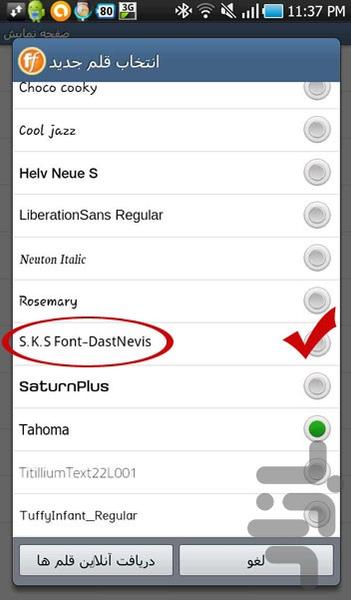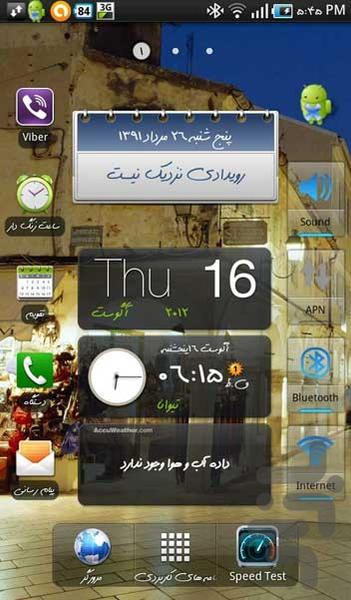
S.K.S-فونت دست نویس Samsung (اصلی)
فونت فارسی برای استفاده در گوشی های دارای سیستم عامل اندروید ، بسیار محدود و دارای تنوع کمی می باشد ، نرم افزار S.K.S-Font-DastNevis فونت زیبای دستنویس فارسی را در گوشی های سامسونگ نصب می نماید و شما براحتی می توانید از این فونت زیبا استفاده نمایید. (این فونت همچنین براحتی امکان حذف را از طریق Uninstall نمودن را دارا می باشد)
نکته2: این فونت کلیه اعداد را نیز فارسی نمایش می دهد.